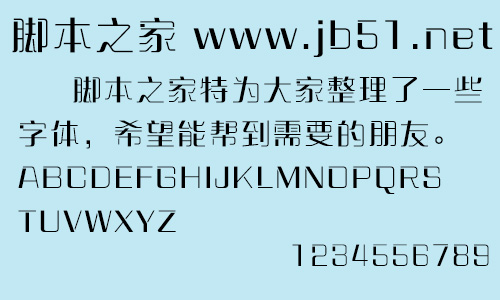
方正晴朗體簡Medium是一款由方正字庫開發(fā)的一款中文藝術(shù)字體,晴朗體普遍每一個字只有兩直劃是粗的,其余橫直都是細(xì)的,左邊上下直角,右邊上下是圓角,形成一個強(qiáng)烈對比,所以粗細(xì)的視覺很平均,適合應(yīng)用于藝術(shù)設(shè)計、平面宣傳設(shè)計、網(wǎng)頁設(shè)計、書法字帖等領(lǐng)域,需要的朋友可以前來本站下載。